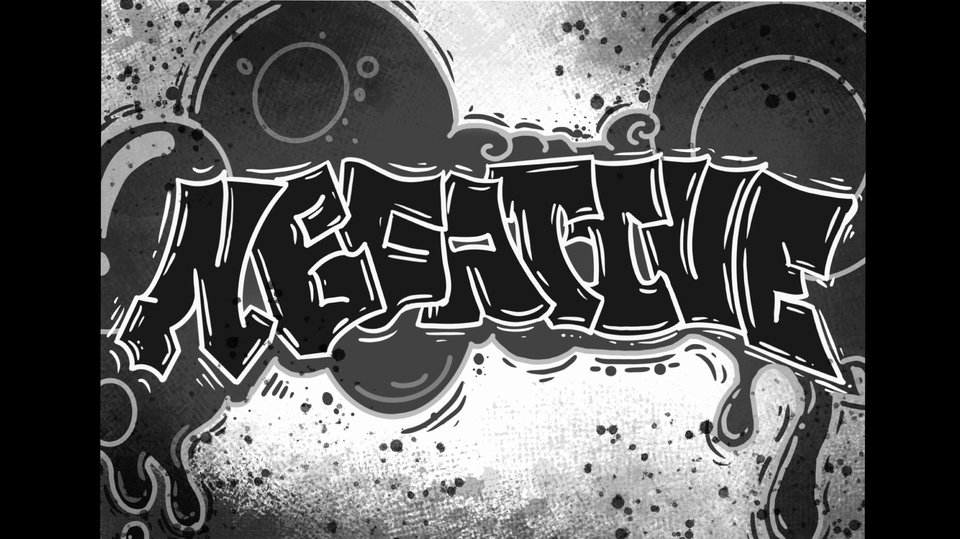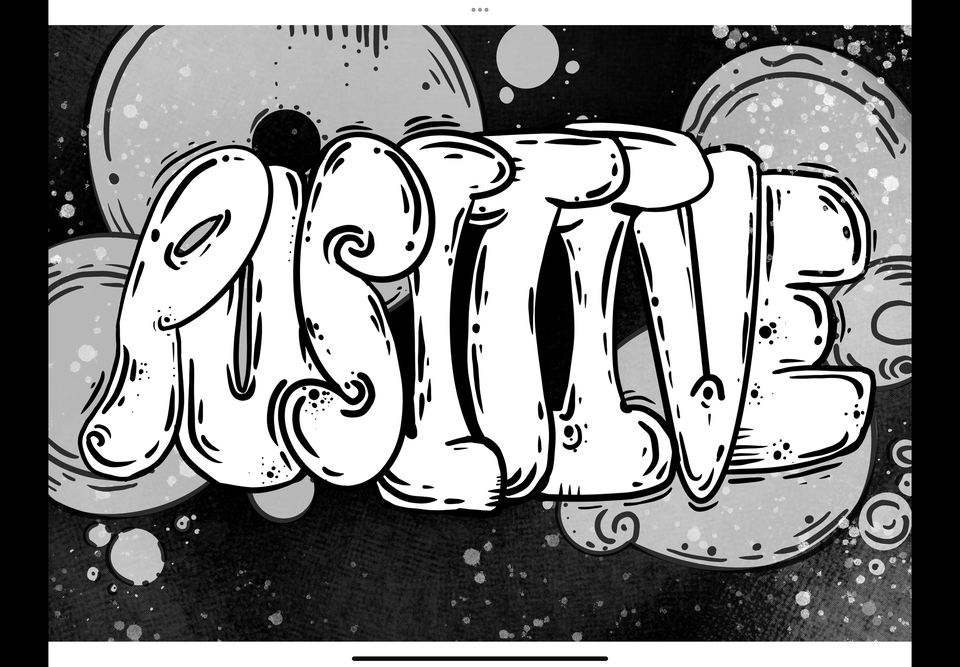
Negative
งานศิลปะกราฟฟิตี้ (Graffiti Art) ขาว-ดำ ทั้งสองภาพสื่อความหมายของ “ด้านลบ” และ “ด้านบวก” ผ่านการใช้ศิลปะตัวอักษรและพื้นหลังที่มีความคอนทราสต์กันอย่างชัดเจน เป็นการสะท้อนแนวคิดเรื่องสมดุลของอารมณ์หรือพลังงานในชีวิต⚪️⚫️ ขั้นตอนการทำงาน 1. ตกลงรายละเอียดเกี่ยวกับผลงาน 2. ส่ง สเก็ตแรกภายใน 12 ชั่วโมง 3. ให้ลูกค้าเลือกโทนสี 4. หากมีการปรับแก้ สามารถแก้ได้ ภายใน 3 ชั่วโมง 5. ถ้างานเสร็จเรียบร้อย ศิลปินจะส่งไฟล์ผลงานให้คุณลูกค้าทันที